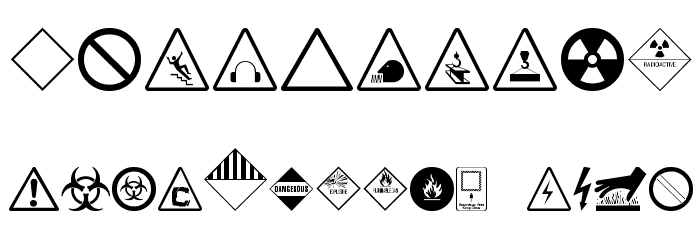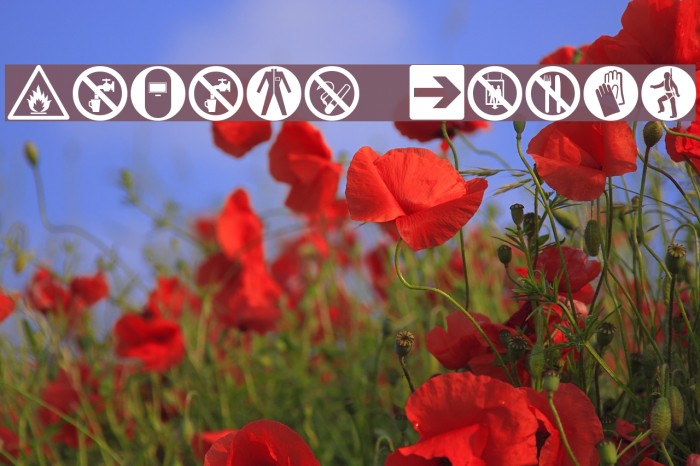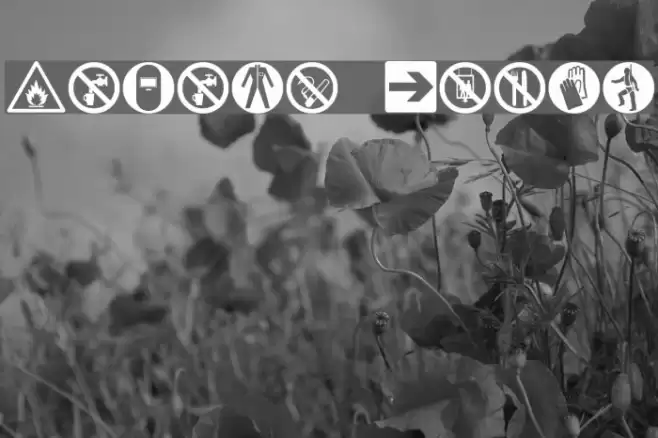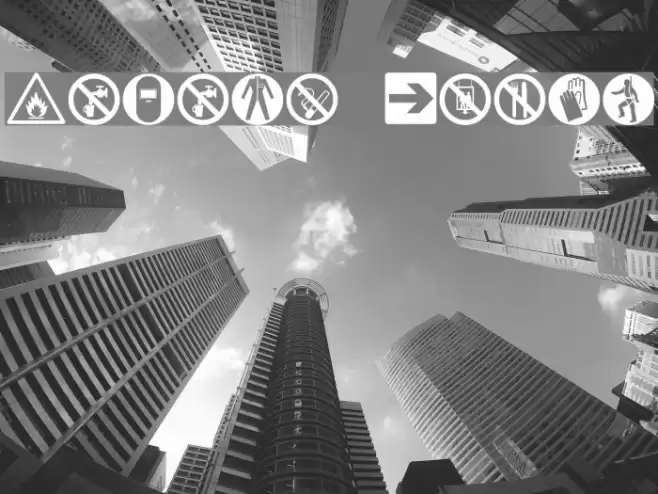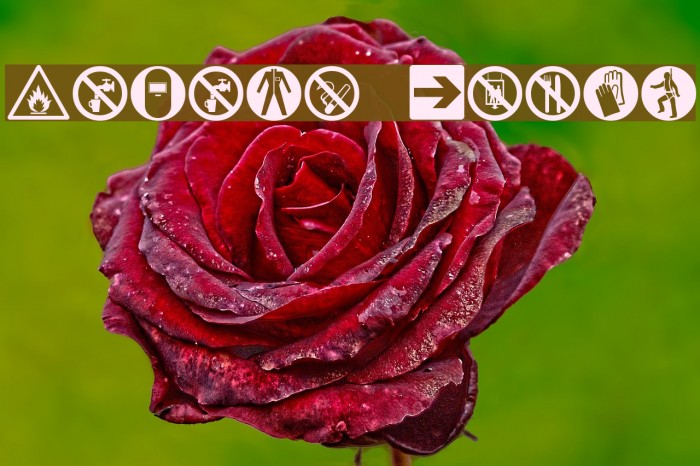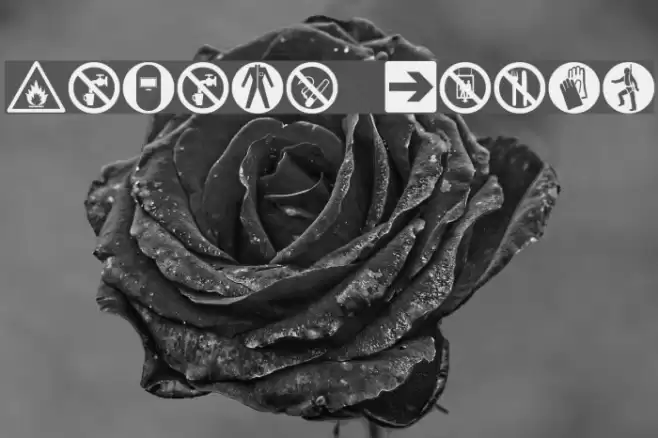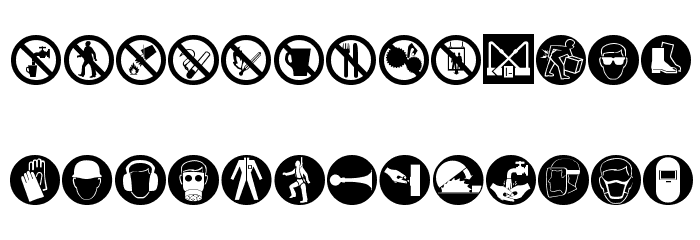
Hazard Signs Font
| Style général | Functional, Modern, Industrial |
| Cas d'utilisation | Signage, Labels, Manuals, Posters |
| Projets proposés | Workplace safety posters, industrial signage, instructional manuals, emergency exit guides, public safety communications. |